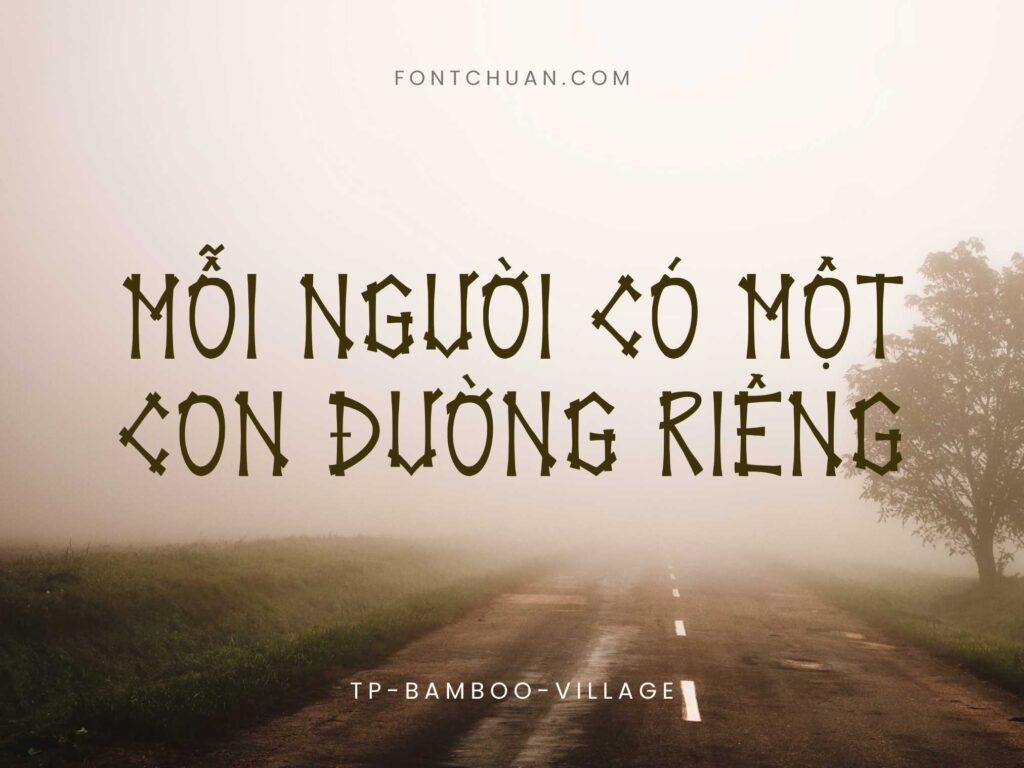
Font TP Bamboo Village Việt Hóa
Tác giả Font: Maulana Creative
Bamboo Village là một font chữ trang trí được thiết kế bởi Maulana Creative. Font này có nét đậm, nhân vật vui nhộn với một số ligatures và alternates, tạo thêm sự sáng tạo cho công việc của bạn. Với phong cách sinh động và phá cách, Bamboo Village cũng có thể được xem là một Font chữ Halloween thú vị, mang lại cảm giác tươi vui nhưng vẫn đậm chất lễ hội cho các thiết kế theo chủ đề. Font đã được Việt hóa để hỗ trợ tiếng Việt bởi Tuỳn Pucca, đồng thời hỗ trợ nhiều ngôn ngữ khác, giúp mở rộng phạm vi sử dụng trên toàn cầu. Font này được sưu tầm và chia sẻ bởi thành viên của Font Chuẩn, đáp ứng nhu cầu của người dùng và ứng dụng thực tế vào các dự án thiết kế.
Đặc điểm thiết kế của Bamboo Village bao gồm các nét đậm và nhân vật vui nhộn, tạo cảm giác thân thiện và sáng tạo. Font này phù hợp cho các ứng dụng như thiết kế logo, mạng xã hội, tiêu đề phim, tiêu đề sách, văn bản ngắn hoặc dài và tốt cho văn bản phụ của bạn với script hoặc serif. Các ngành nghề phù hợp bao gồm quảng cáo, nghệ thuật và thiết kế đồ họa.